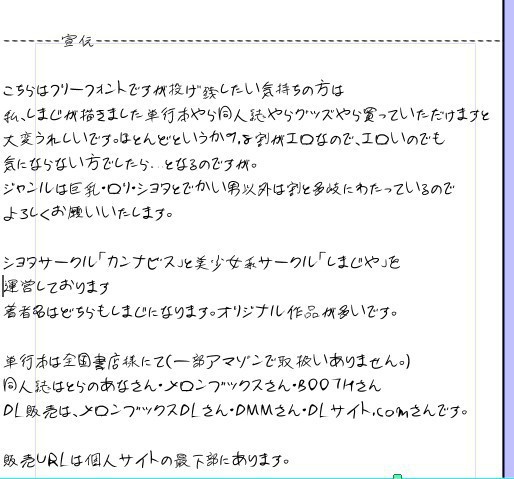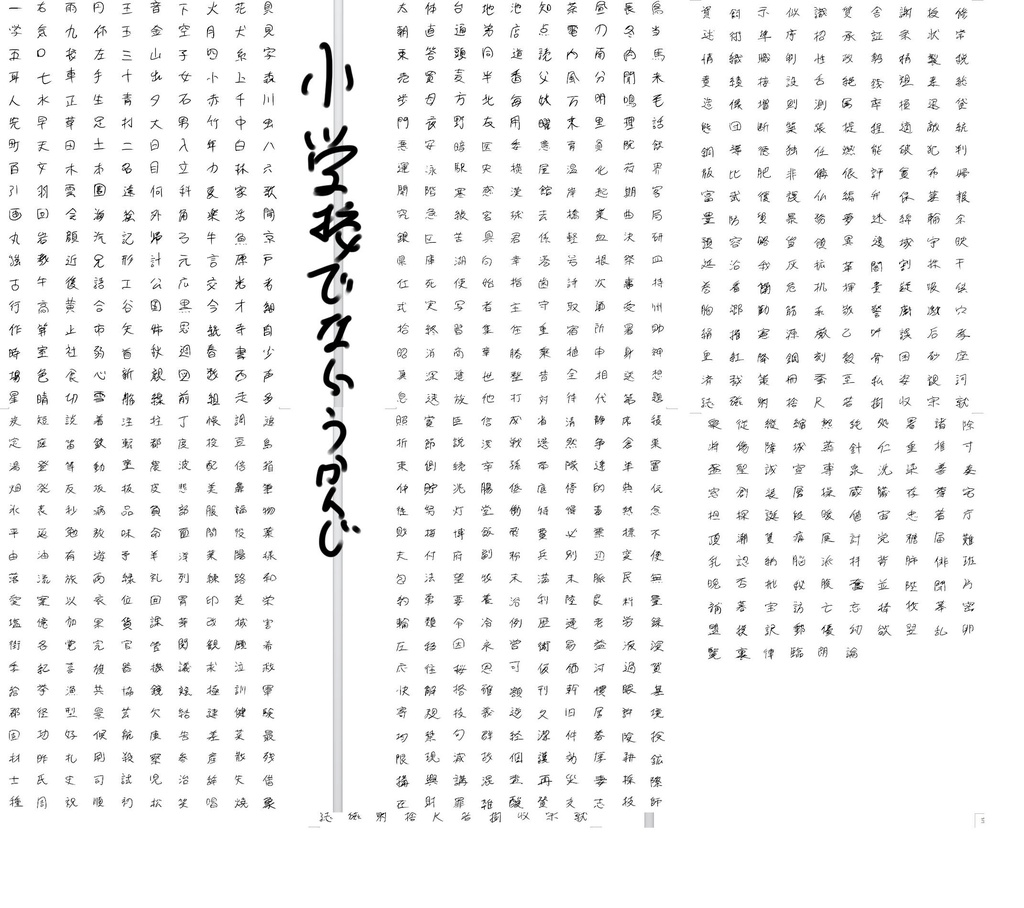
私、しまじがかきました手書きフォントです。 漫画等でキャラが描いた汚い字が必要な時とかにどうぞ。 ひらがな改良前(より汚い)2.0とひらがな改良後の2.1同梱です。 フォント作った作れるサイトが閉鎖したので、こちらのアップデートは今後ありません。 個人・商用利用ともに無料で利用できます。クレジット表記や事前連絡は必要ありません。ただし、フォントの著作権は放棄しておりません。フォントデータを販売する行為や無断での再配布を禁止します。 ご使用によるトラブルや損害等に一切の責任を負いません。 また、使用規約が守られてない際にフォントファイルを予告なしに削除・変更することがありますのでご了承ください。 OK Webサイトの画像への文字入れ 印刷物のデザインに使用 LINEスタンプ、WEBフォント 商品のラベル、パッケージ 動画・映像の文字入れ PDF、ソフトウェアへの埋め込み、ゲームへの使用 ロゴ(商標登録はできません) NG 実写アダルト作品への利用(イラスト、漫画、3DCG等はOK) フォントファイルの再配布(書籍の付録等に収録する場合は、事後連絡で構いませんのでご一報ください) 自作発言・商標登録 特定の個人、団体への差別、中傷に使用すること 他、公序良俗に反するもの フォントデータへの直リンク -------宣伝------------------------------------------------------------------------------------ こちらはフリーフォントですが投げ銭したい気持ちの方は 私、しまじが描きました単行本やら同人誌やらグッズやら買っていただけますと 大変うれしいです。ほとんどというか9.8割がエロなので、エロいのでも 気にならない方でしたら…となるのですが。 ジャンルは巨乳・ロリ・ショタとでかい男以外は割と多岐にわたっているのでよろしくお願いいたします。 ショタサークル「カンナビス」と美少女系サークル「しまじや」を運営しております 著者名はどちらもしまじになります。オリジナル作品が多いです。 単行本は全国書店様にて(一部アマゾンで取扱いありません。) 同人誌はとらのあなさん・メロンブックスさん・BOOTHさん DL販売は、メロンブックスDLさん・DMMさん・DLサイト.comさんです。 販売URLは個人サイトの最下部にあります。 http://simajiya.wixsite.com/index (18禁注意)